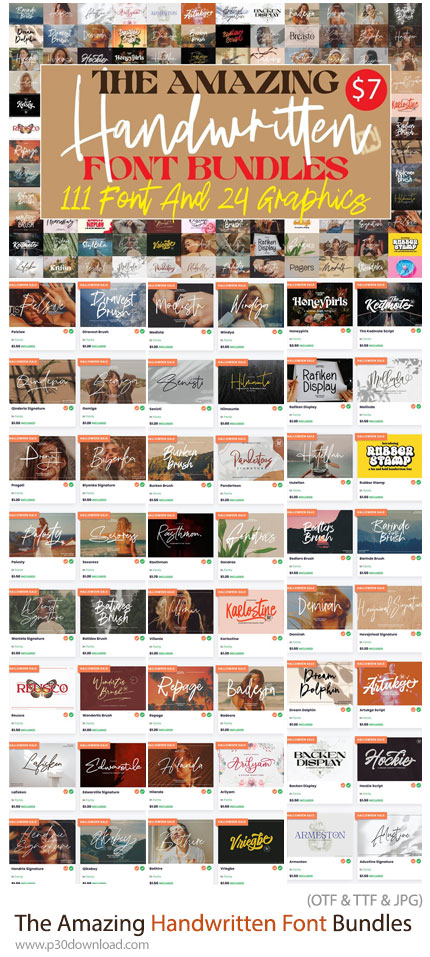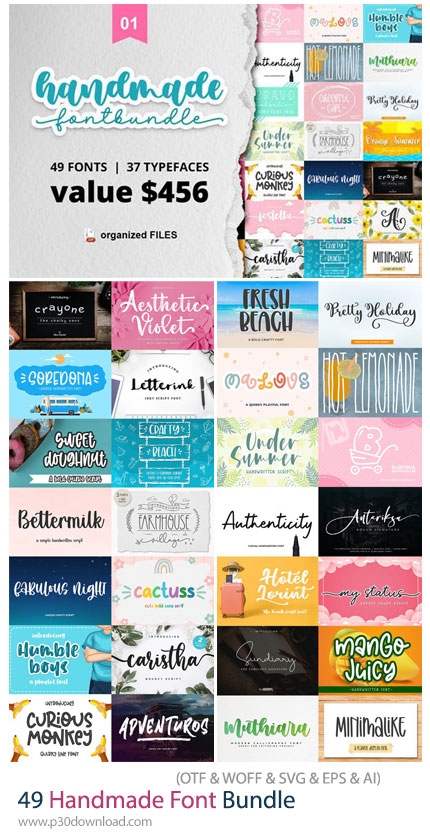
دانلود Font & Bonus Bundle - مجموعه 40 فونت انگلیسی حرفهای و خلاقانه: / در این مطلب شاهد مجموعه 40 فونت انگلیسی حرفهای و خلاقانه می باشید که با فرمت مجموعه Font & Bonus Bundle یک پک متنوع از فونتهای حرفهای و خلاقانه است که با در اختیار قرار دادن مجموعهای از فونتهای مختلف، گزینههای متعددی برای طراحی پروژههای گرافیکی فراهم میکند. این مجموعه میتواند برای طراحانی که به دنبال تنوع تایپوگرافی و دسترسی سریع به سبکهای متفاوت فونت هستند، کاربردی باشد و در پروژههای چاپی و دیجیتال مورد استفاده قرار گیرد. وجود فونتهای متنوع در این باندل، امکان انتخاب سبک مناسب برای هر نوع طراحی را فراهم میکند؛ از طراحی عنوان و تیتر گرفته تا پوستر، لوگوتایپ، بستهبندی، محتوای شبکههای اجتماعی، کارت ویزیت، بروشور و پروژههای تبلیغاتی. فونتها را میتوان در نرمافزارهای گرافیکی مختلف مانند Adobe Photoshop و Adobe Illustrator و دیگر نرمافزارهای طراحی مورد استفاده قرار داد. این مجموعه فونت میتواند برای طراحی پوسترهای تبلیغاتی، کاور شبکههای اجتماعی، عنوان و تیتر، لوگو و لوگوتایپ، بستهبندی محصولات، کارت دعوت، کارت ویزیت، بروشور، بنر، طراحی برند و محتوای دیجیتال مورد استفاده قرار گیرد. تنوع موجود در یک پک واحد باعث میشود برای پروژههای مختلف نیازی به جستوجوی جداگانه برای فونتهای متفاوت نداشته باشید. ...
دانلود Haunting & Weird Premium Fonts Pack - مجموعه 20 فونت انگلیسی ترسناک، عجیب و خاص برای طراحی: / در این مطلب شاهد 20 فونت انگلیسی ترسناک، عجیب و خاص برای طراحی می باشید که با فرمت TTF بر روی سایت برای دانلود قرار گرفته است. این مجموعه فونت پریمیوم با طراحیهای خاص، عجیب، مرموز و ترسناک است که برای پروژههای گرافیکی با فضای متفاوت و غیرمعمول طراحی شدهاند. این مجموعه با تنوع در فرم حروف و سبکهای بصری، گزینهای مناسب برای ایجاد تایپوگرافیهای چشمگیر و انتقال حس ترس، رمزآلودگی، تاریکی و هیجان در طراحی است. این فونتها میتوانند به شما کمک کنند برای عناوین و نوشتههای مهم، هویت بصری متفاوتی ایجاد کنید و فضای پروژه را با استفاده از تایپوگرافی مناسب تقویت کنید. از طراحی پوسترهای ترسناک و آثار مرتبط با هالووین گرفته تا کاور آلبوم، عنوان فیلم و محتوای هنری، این مجموعه کاربردهای متنوعی دارد. از این مجموعه میتوانید در طراحی پوستر فیلمهای ترسناک، پروژههای هالووین، کاور موسیقی، پوسترهای دارک، بازیهای ویدیویی، عناوین سینمایی، آثار هنری، تیزرهای تبلیغاتی و محتوای شبکههای اجتماعی استفاده کنید. انتخاب یک فونت مناسب در چنین پروژههایی میتواند نقش مهمی در انتقال حس و فضای کلی اثر داشته باشد. این مجموعه گزینهای مناسب برای طراحانی است که به دنبال مجموعهای از فونتهای متفاوت و غیرمتعارف برای ایجاد طرحهای ترسناک، عجیب، مرموز و تاریک هستند و میخواهند تایپوگرافی پروژه آنها بخشی از فضای بصری و داستان اثر باشد. ...
دانلود Ultimate Mega Font Bundle - مجموعه 30 فونت انگلیسی حرفهای و متنوع: / در این مطلب شاهد 30 فونت انگلیسی حرفهای و متنوع می باشید که با فرمت های OTF و TTF و JPG بر روی سایت برای دانلود قرار گرفته است. Ultimate Mega Font Bundle یک مجموعه بزرگ و کاربردی از فونتهای متنوع برای طراحان گرافیک، تولیدکنندگان محتوا و علاقهمندان به طراحی تایپوگرافی است. این باندل با گردآوری مجموعهای از سبکهای مختلف فونت، امکان انتخاب و استفاده از تایپفیسهای مناسب برای پروژههای گوناگون را در اختیار شما قرار میدهد. تنوع سبک در یک مجموعه فونت بزرگ به طراح کمک میکند برای هر پروژه، متناسب با فضای بصری و هویت برند، فونت مناسب را انتخاب کند. از طراحی لوگو و هویت بصری گرفته تا پوستر، بستهبندی، تبلیغات، شبکههای اجتماعی، طراحی تیشرت، کارت دعوت و پروژههای چاپی، میتوان از فونتهای این مجموعه برای ایجاد ترکیبهای تایپوگرافیک متفاوت استفاده کرد. این مجموعه برای طراحانی که به دنبال گسترش کتابخانه فونتهای خود هستند گزینهای مناسب است و میتواند در نرمافزارهای طراحی و گرافیکی مختلف مورد استفاده قرار گیرد. وجود سبکهای متنوع باعث میشود بتوان از فونتها در پروژههای مدرن، مینیمال، کلاسیک، دستنویس، تزئینی، تبلیغاتی و خلاقانه استفاده کرد. این پک فونت انگلیسی انتخابی مناسب برای طراحانی است که میخواهند یک مجموعه متنوع از فونتها را در اختیار داشته باشند و برای هر پروژه، از طراحی لوگو و برندینگ گرفته تا تبلیغات، پوستر، شبکههای اجتماعی و محصولات چاپی، گزینههای تایپوگرافی بیشتری در دسترس داشته باشند. ...
دانلود The Amazing Handwritten Font Bundles - 111 فونت دست نویس انگلیسی با طراحی شگفت انگیز: / پکیج فونتهای دست نویس انگلیسی، یک مجموعه شامل چندین فونت دستنویس زیبا و منحصر به فرد است. این باندل شامل مجموعهای از فونتهای با خط دستی زیبا میشود که به طراحان گرافیکی و تایپوگرافیک امکان ایجاد اثرات دستنویسی و نگارشهای ظاهری واقعگرا را میدهد. هر فونت این باندل دارای طرحها، خطوط و اندازههای متفاوتی میباشد که به شما انعطافپذیری در طراحیها و انتخابهای متنوع میدهد. این فونتهای دستنویس برای ایجاد استایلهای متنوع و خلاق در طرحها، لوگوها، بنرها، پوسترها و سایر پروژههای گرافیکی بسیار مناسب هستند. از دیگر ویژگیهای این پکیج، امکان تغییر رنگها، اندازهها و سفارشیسازی نیز در این فونتها وجود دارد که این امر به شما اجازه میدهد تا بهترین شکل ممکن با نیازهای پروژههای خود هماهنگ شوید. اگر به دنبال فونتهای دستنویس خلاقانه و منحصر به فرد هستید، این پکیج فونتهای دستنویس را در اختیار دارید که به طراحیها و محتواهای شما زندگی و حالت بصری خاصی میبخشد. این پکیج به تمامی طراحان گرافیک و تایپوگرافیکی و همچنین افرادی که به دنبال انعطافپذیری و زیبایی در استفاده از فونتها هستند توصیه میشود که با فرمت های OTF و TTF بر روی سایت برای دانلود قرار گرفته است. ...
دانلود Mix Fonts Bundle - مجموعه فونتهای انگلیسی متنوع و حرفهای: / در این مطلب شاهد مجموعه فونتهای انگلیسی متنوع و حرفهای می باشید که با فرمت های OTF و TTF و JPG بر روی سایت برای دانلود قرار گرفته است. Mix Fonts Bundle یک مجموعه جامع از فونتهای خلاقانه و کاربردی است که شامل سبکهای متنوع تایپوگرافی برای استفاده در پروژههای طراحی گرافیک، برندینگ، تبلیغات و تولید محتوا میباشد. این پک با گردآوری مجموعهای از فونتهای مدرن، کلاسیک، دستنویس، نمایشی و حرفهای، ابزار مناسبی برای طراحانی است که به دنبال تنوع بالا در انتخاب تایپفیس هستند. این مجموعه به شما کمک میکند برای هر نوع پروژه، از طراحی لوگو و هویت بصری گرفته تا پوستر، شبکههای اجتماعی و محصولات چاپی، فونت مناسب را سریعتر پیدا کنید. این پک فونت یک آرشیو کاربردی از فونتهای متنوع برای طراحانی است که میخواهند مجموعهای گسترده از سبکهای تایپوگرافی را در اختیار داشته باشند. این پک با ارائه فونتهای خلاقانه و حرفهای، امکان طراحی پروژههای متنوع از لوگو و تبلیغات تا محتوای دیجیتال و چاپی را فراهم میکند. ...
دانلود Handmade Font Bundle - 49 فونت انگلیسی دست نویس: / در این مطلب شاهد 49 فونت انگلیسی دست نویس می باشید که با فرمت های OTF و WOFF و SVG و EPS و AI و JPG بر روی سایت برای دانلود قرار گرفته است. Handmade Font Bundle یک پکیج حرفهای شامل 49 فونت دستساز (Handmade & Script Fonts) است که برای ایجاد طراحیهای طبیعی، هنری و خلاقانه استفاده میشود. این فونتها حس واقعی دستنویس بودن را منتقل میکنند و برای برندینگهای صمیمی و طراحیهای احساسی بسیار مناسب هستند. Handmade Font Bundle یک مجموعه کامل از فونتهای دستساز و خلاقانه است که به طراحیهای شما حس انسانی، طبیعی و هنری میدهد و برای برندینگ و محتوای بصری بسیار کاربردی است. ...
دانلود Meshkal Arabic Font - فونت عربی مشکال: / در این مطلب شاهد فونت عربی مشکال می باشید که با فرمت OTF بر روی سایت برای دانلود قرار گرفته است. Meshkal یک فونت نمایشی (Display Font) عربی با طراحی منحصربهفرد و مدرن است که از الگوها و ساختارهای هندسی کالیدوسکوپی (Kaleidoscopic Geometries) الهام گرفته شده است. نام این فونت از واژه عربی «مشکال» به معنای کالیدوسکوپ گرفته شده و بهخوبی بازتابدهنده سبک هندسی و چشمنواز آن است. این فونت با ساختاری مستحکم، خطوط ضخیم و لبههای تیز طراحی شده و برای پروژههایی که نیاز به تایپوگرافی شاخص، مدرن و متفاوت دارند، گزینهای ایدهآل محسوب میشود. طراحی خاص Meshkal باعث میشود در عناوین، پوسترها، برندینگ و پروژههای گرافیکی جلوهای قدرتمند و متمایز ایجاد کند. اگر به دنبال یک فونت عربی با هویت هندسی، مدرن و متفاوت هستید، Meshkal Arabic Font با الهام از ساختارهای کالیدوسکوپی و طراحی قدرتمند خود میتواند انتخابی عالی برای پروژههای تایپوگرافی، پوستر، برندینگ و طراحیهای خلاقانه باشد. ...